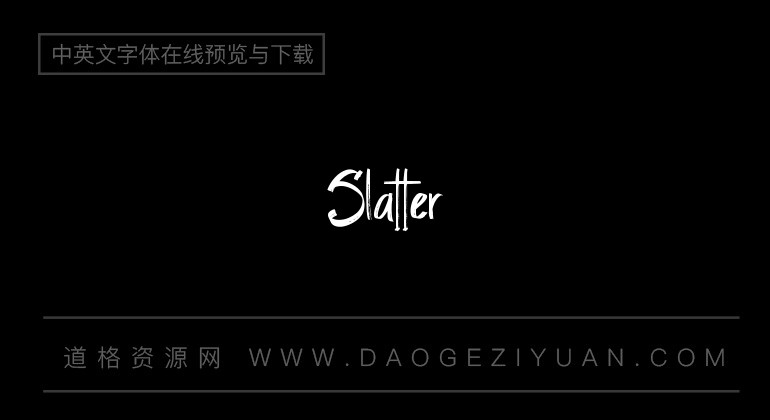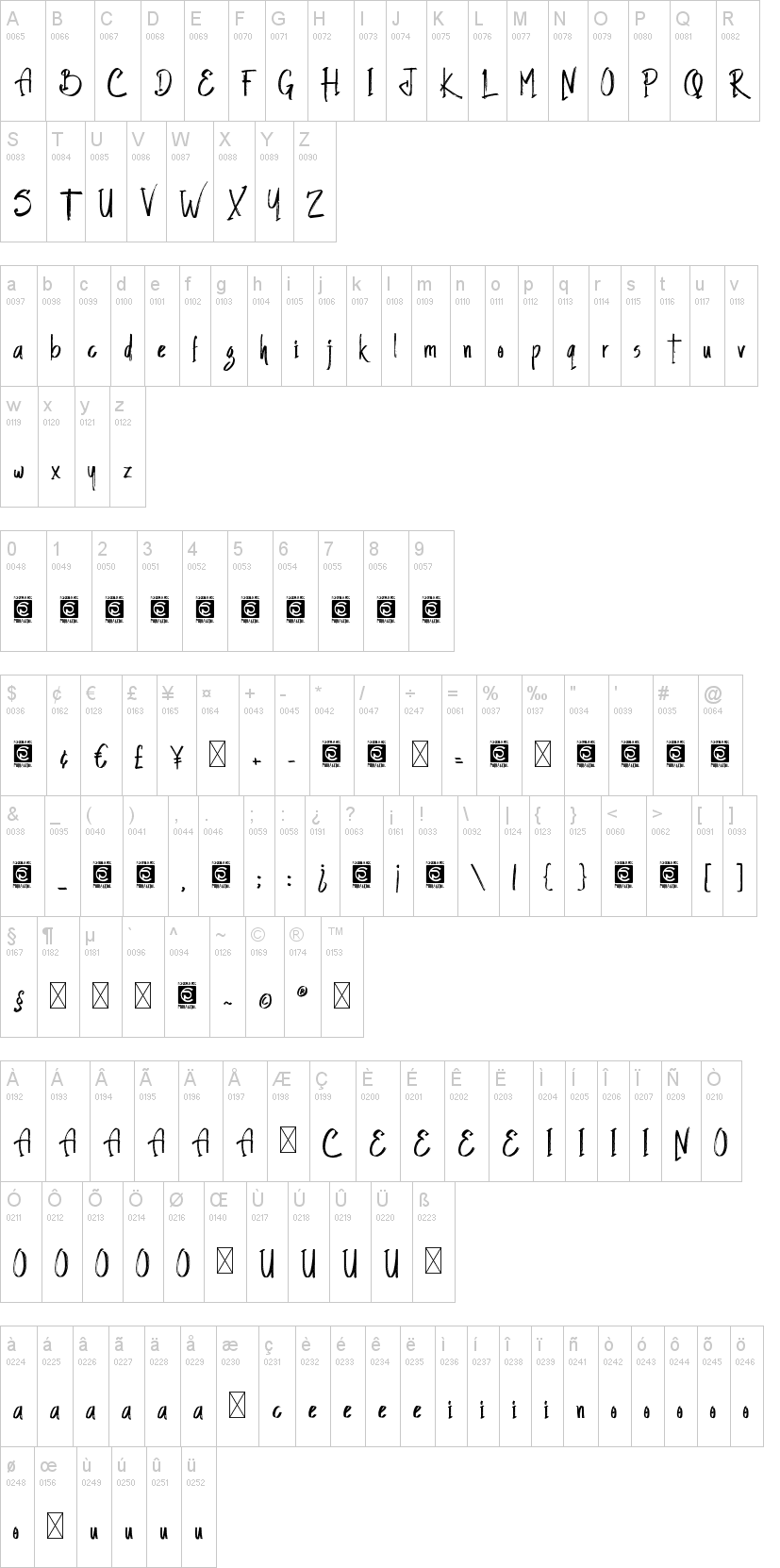
Slatter 字体是一款非常优雅的欧美风格字体,它由英国设计师 Alex Slatter 创作,它具有清晰的细节和柔和的线条,拥有精致的英文字符,可以用来制作海报、标志和其他图形设计。它的特点是它的笔画细腻,字形简洁,可以营造出一种温暖的气氛,是一款非常适合用于品牌推广的字体。内容介绍
Slatter是一款非常不错的手写艺术字体,具有很好的视觉感,适合于文化类的宣传设计、商业类品牌的广告和产品包装设计以及个性化文字排版等较多场景。